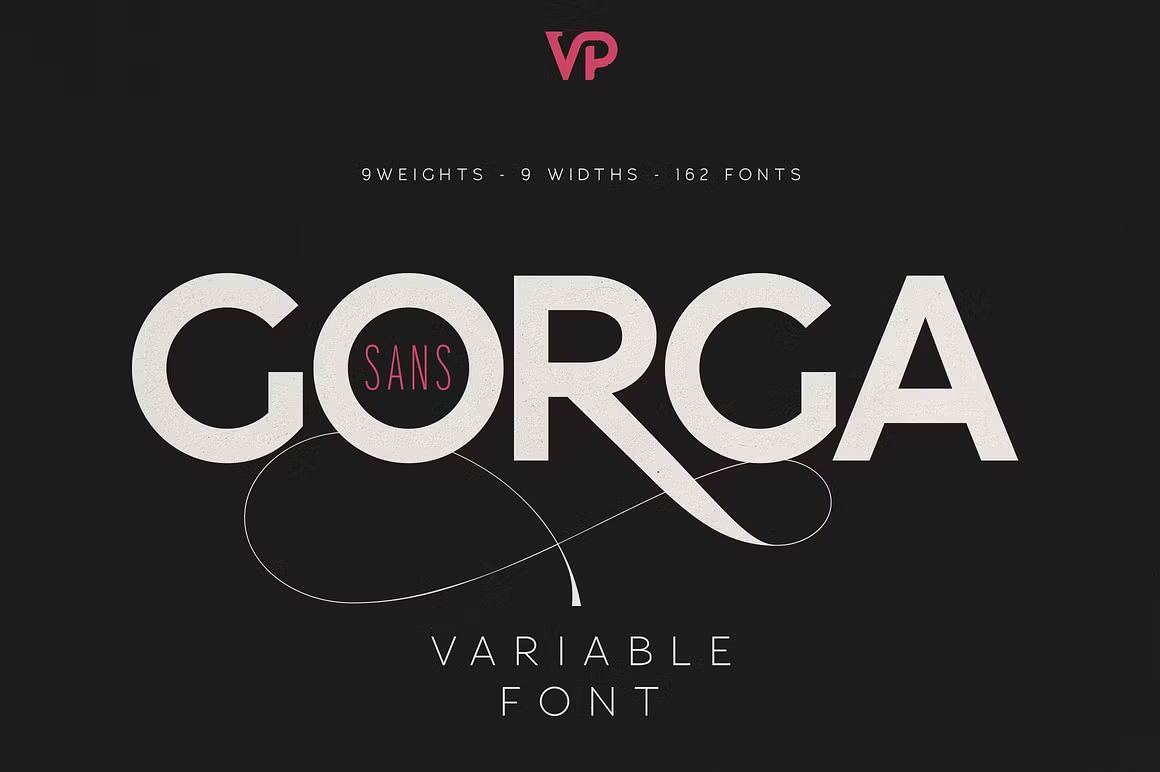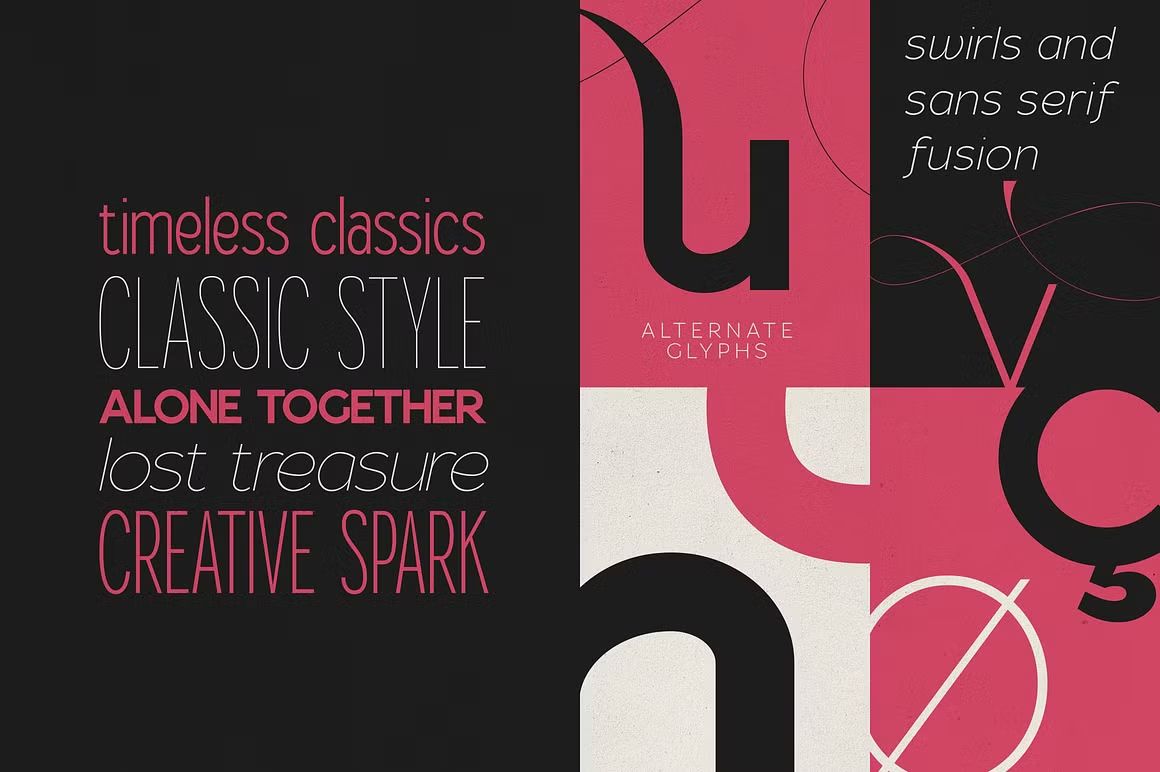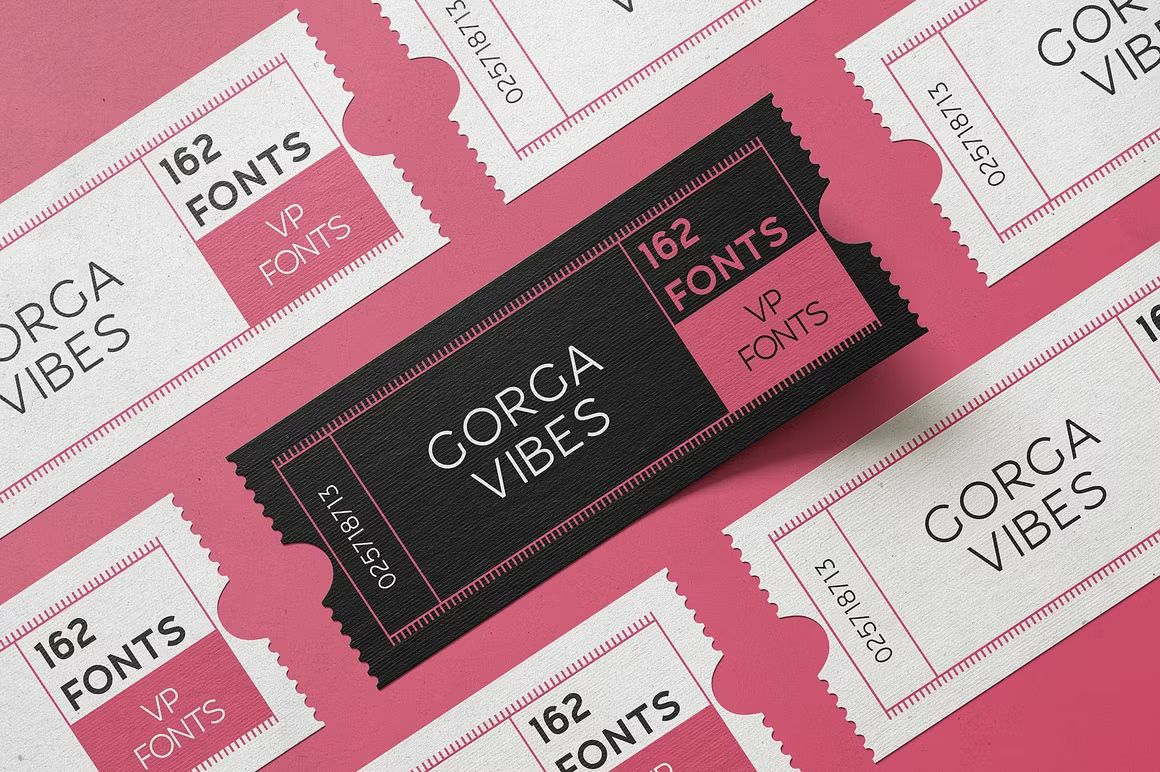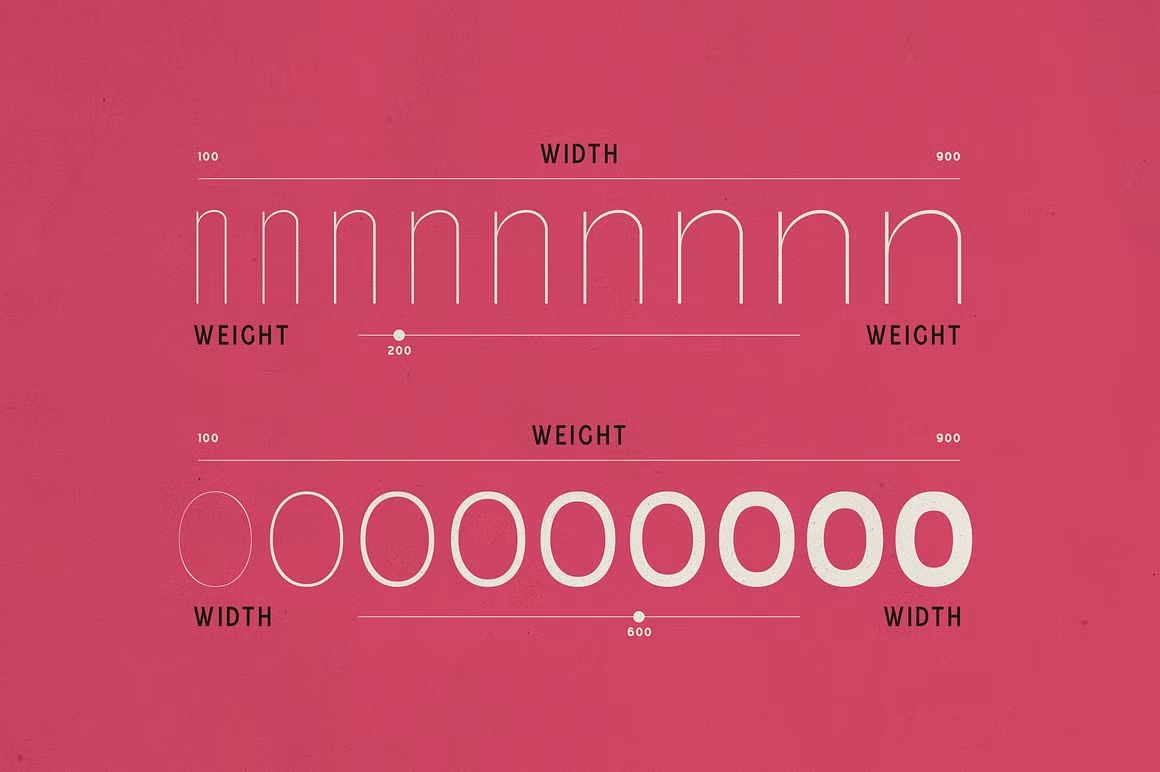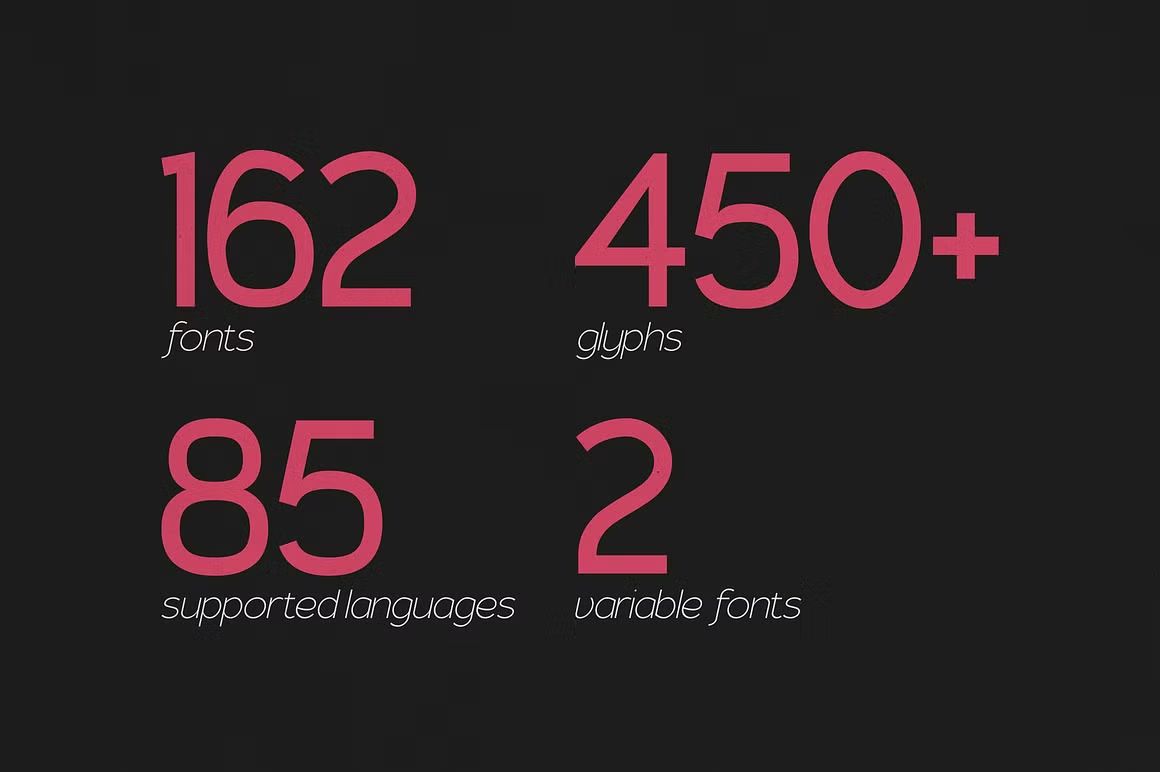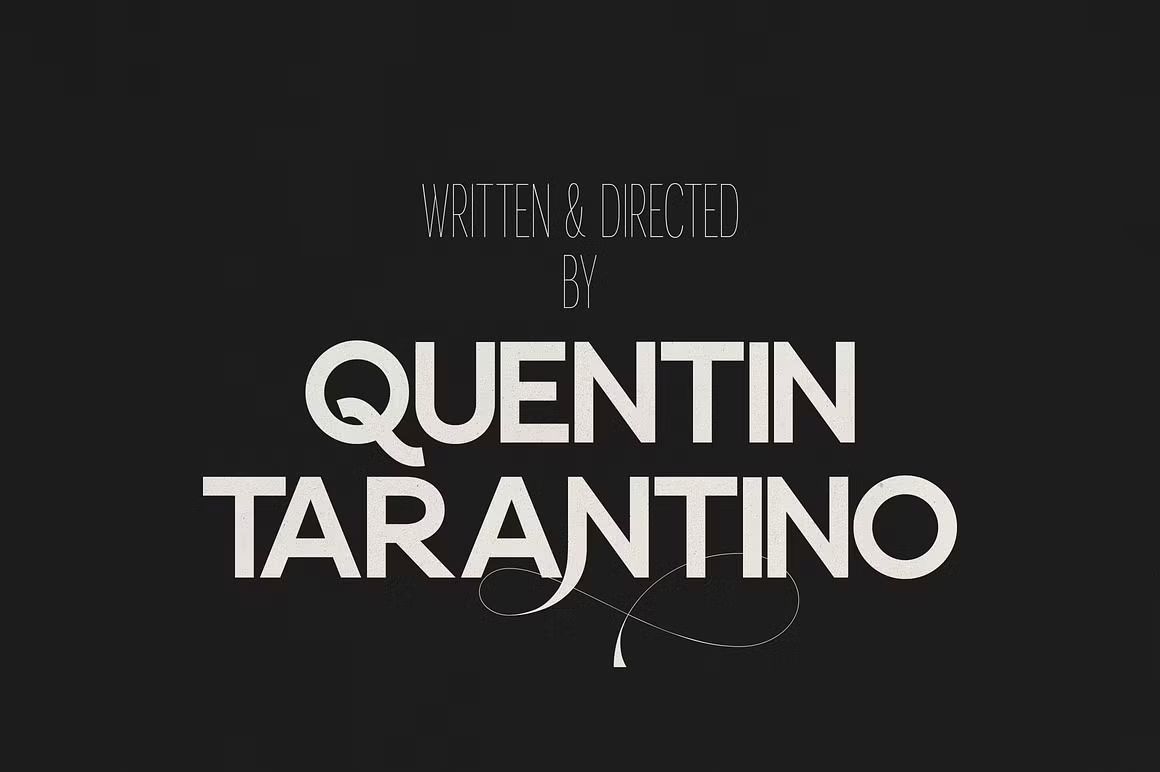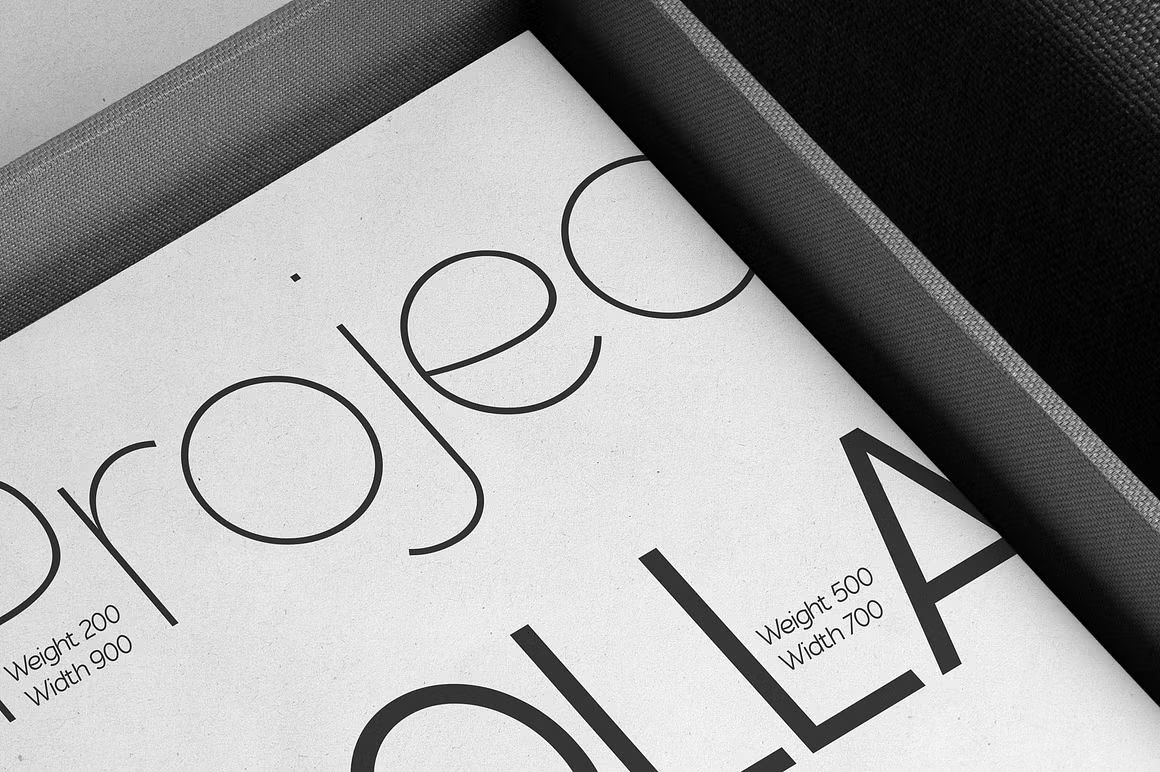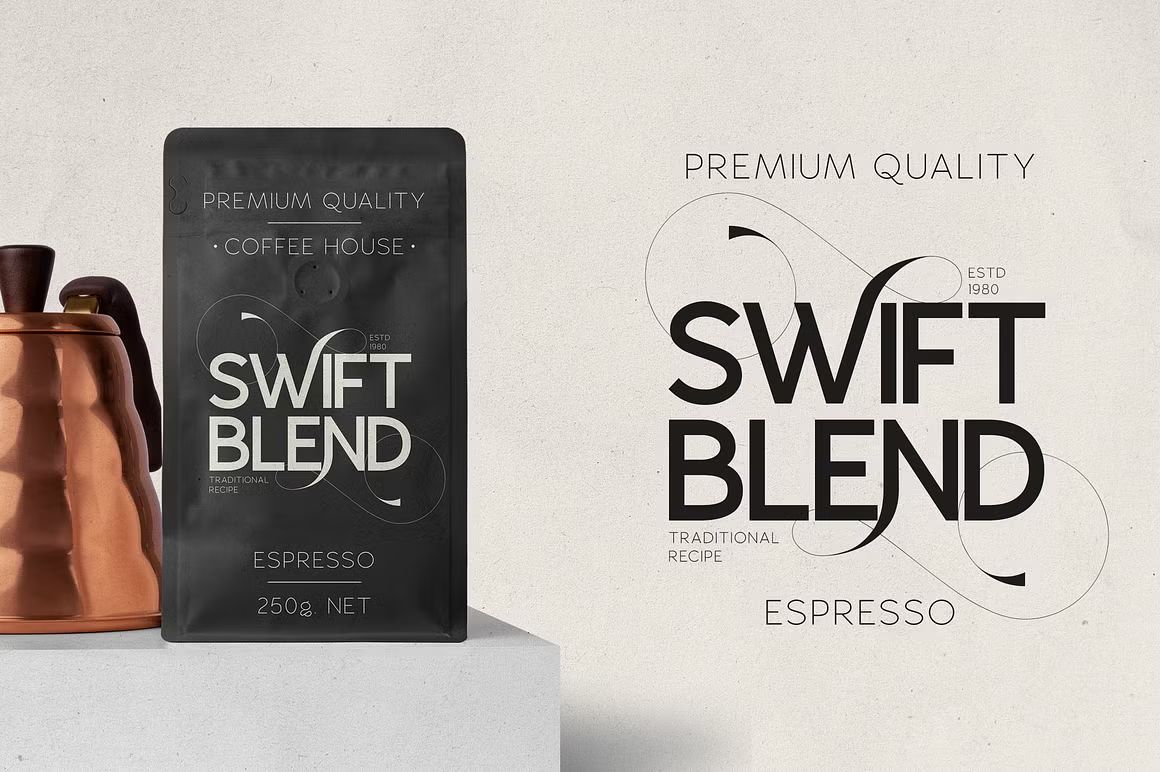
Gorga – Sans Serif Font
Gorga adalah font sans serif modern dengan tampilan yang bersih, kuat, dan fleksibel. Dengan bentuk huruf yang tegas namun tetap elegan, Gorga cocok digunakan untuk branding, judul, desain editorial, UI/UX, dan kemasan produk. Desainnya yang minimalis namun berkarakter menjadikan font ini ideal untuk proyek visual yang mengutamakan kejelasan dan daya tarik profesional.
• Sans serif tegas dengan gaya modern dan versatile
• Cocok untuk branding, editorial, dan tampilan digital
• Termasuk huruf besar, kecil, angka, dan simbol